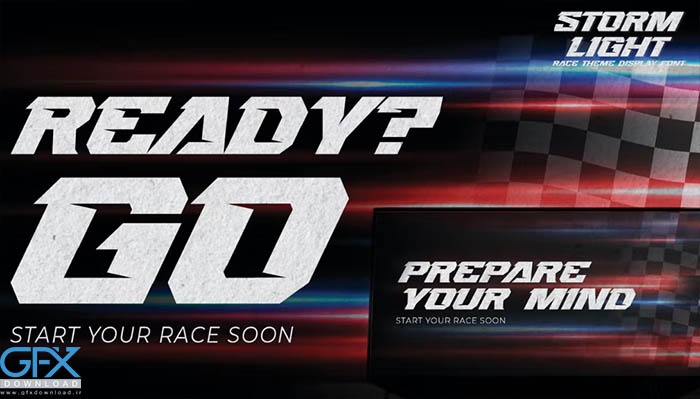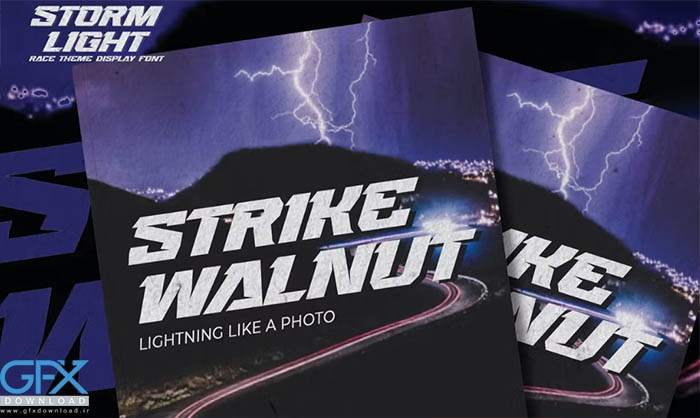
در این پست با معرفی یک فونت جدید STORMLIGHT که یک فونت نمایش با تم مسابقه است با شما همراه هستیم. این فونت نمایشی دست ساز با لمسی شیک که از لوگوی مینیمالیستی معروف الهام گرفته شده است. فونت مسابقه ای STORMLIGHT برای اهداف طراحی قالب، بروشور، ویدئو، برندسازی تبلیغاتی، لوگو و موارد دیگر بسیار مناسب است. این فونت ورزشی با تفاوت های ظریف و قوی است.
این فونت انگلیسی ورزشی و مسابقه برای پروژه های خلاقانه بعدی شما مانند لوگوها، نقل قول های چاپ شده، دعوت نامه ها، کارت ها، بسته بندی محصول، سربرگ ها، لوگوتایپ، سربرگ، پوستر، برچسب و غیره عالی است. به صورت دستی و با عشق ساخته شده است. برای هر پروژه طراحی مانند دعوت، جلد کتاب، کاردستی یا هر هدف طراحی مناسب است.